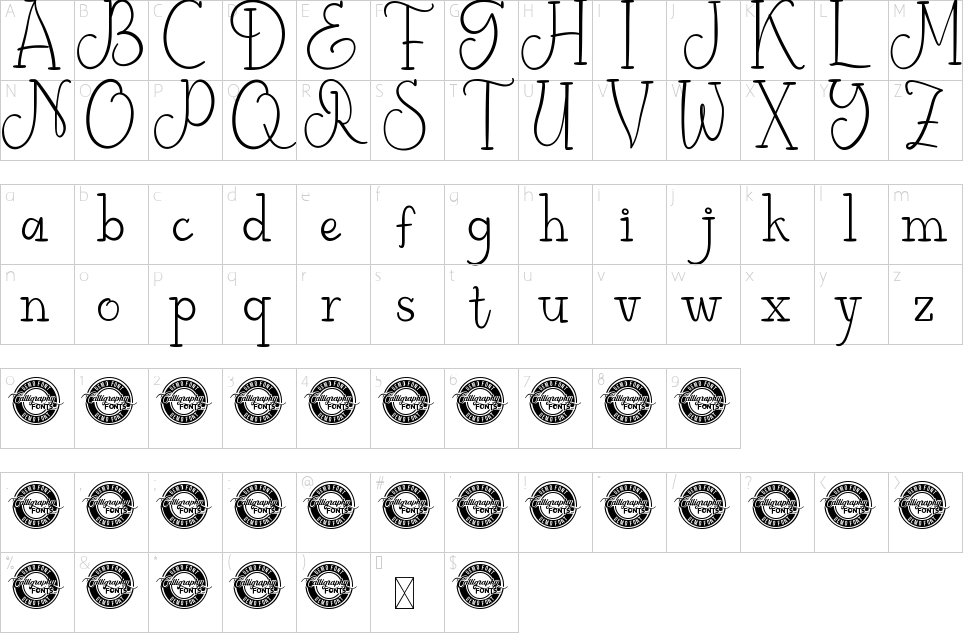
Descubra Magic Stunning, uma fonte única e poderosa que vai enriquecer o visual de seus projetos. Desenvolvida por CalligraphyFonts, Magic Stunning combina elegância e originalidade para criar textos memoráveis. Essa fonte é uma escolha ótima para aqueles que buscam uma solução versátil e sofisticada. Com o download de Magic Stunning, você adiciona um toque especial a qualquer projeto, seja em seu site pessoal, blog ou mesmo em um projeto empresarial. Desde os textos mais simples até as imagens mais elaboradas, Magic Stunning se destaca como uma opção de alta qualidade. Obrigado a todos os 677 pessoas que já tiveram o privilégio de experimentar Magic Stunning, e estamos felizes em oferecer essa fonte maravilhosa de graça. Não perca tempo, crie algo incrível com Magic Stunning.